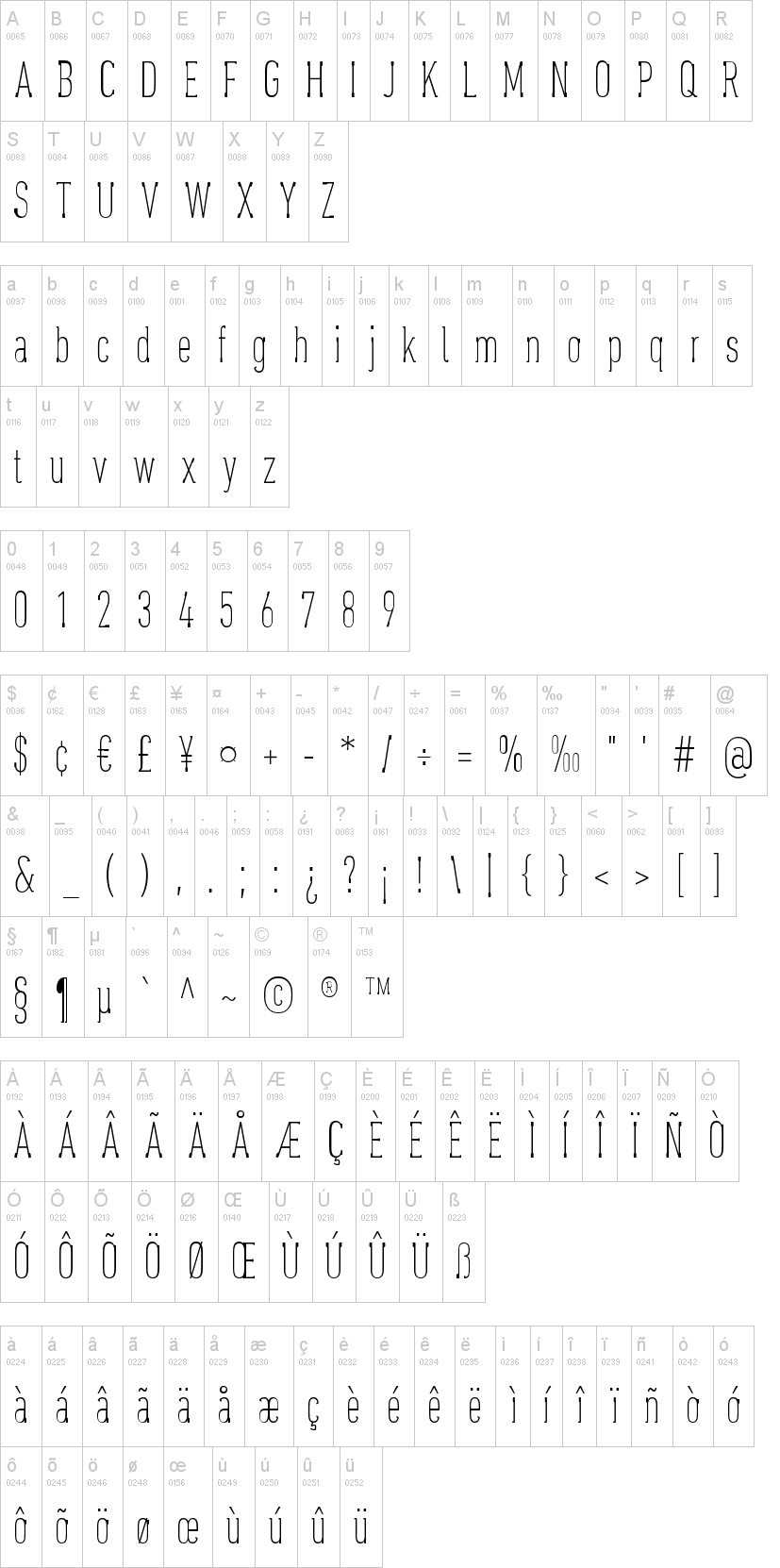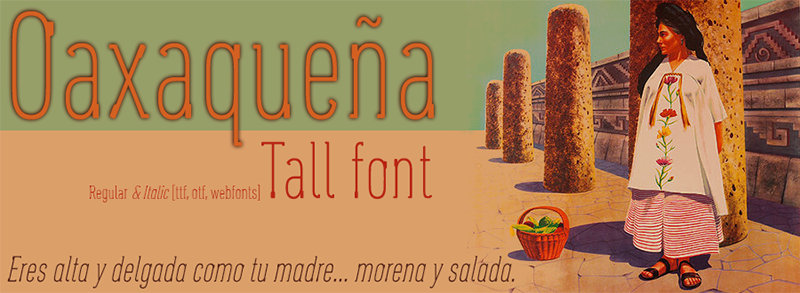
Шрифт Oaxaqueña Tall
Tipografía extra fina y extra condensada, rematada con pequeños serif verticales de acabado redondeado. Mayo de 2013.
El nombre de la tipografía rinde tributo a la mujer mexicana natural del estado de Oaxaca (ejemplo multicultural donde conviven más de 15 etnias indígenas) ¡Eeeres alta y delgada como tu maaadre, mooorena y saaaladaaa!